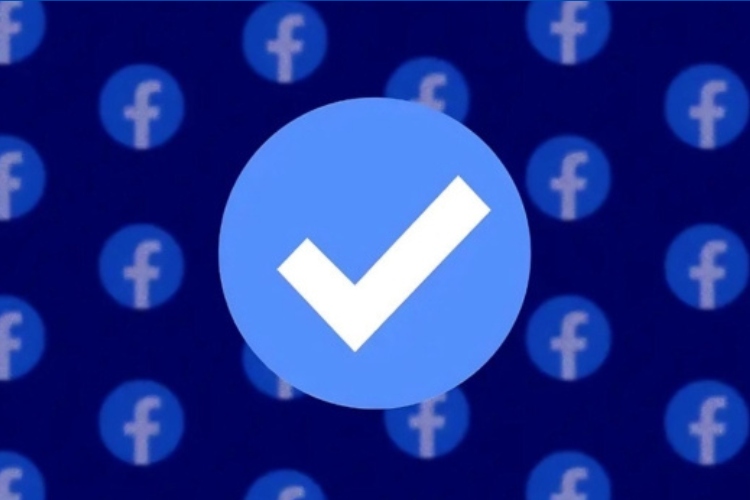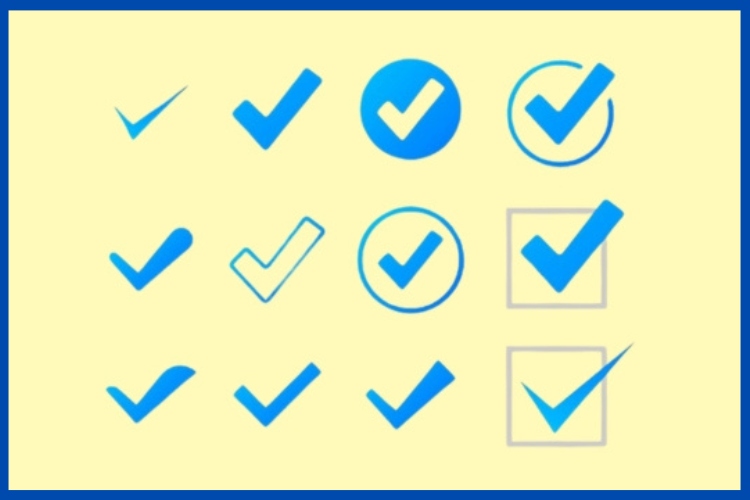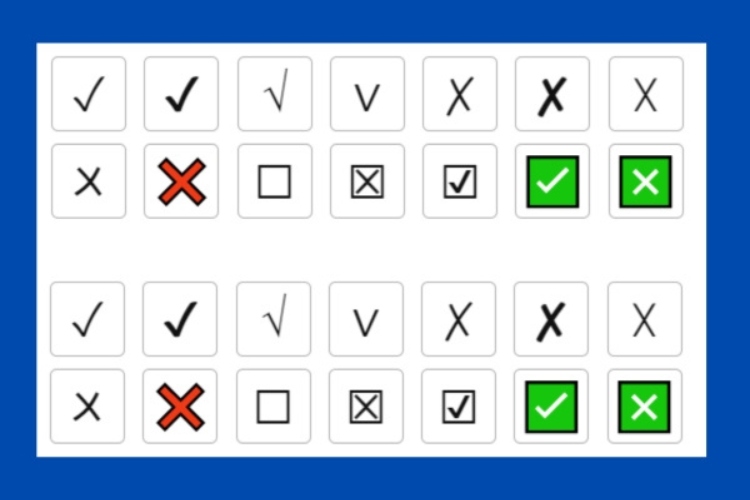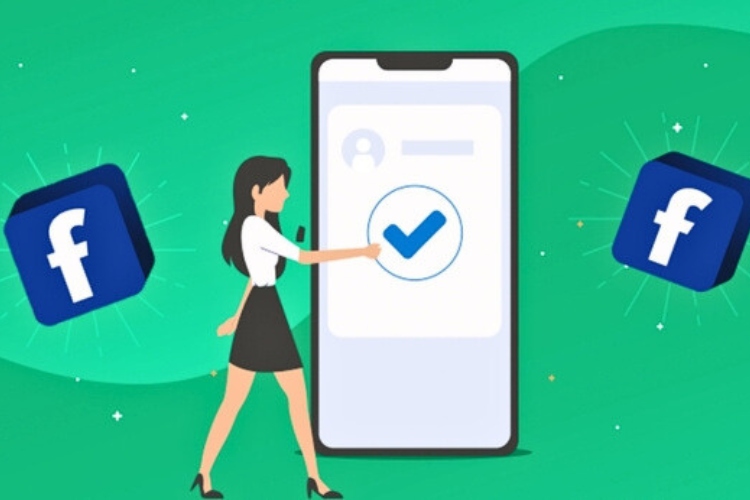
777+ kí tự tích xanh đẹp trên Facebook, TikTok, Telegram không thể bỏ lỡ
Kí tự tích xanh là biểu tượng hình chữ "V" cách điệu hoặc dấu tick, thường được hiển thị dưới dạng: ✅, ✔️, hoặc ✓. Hơn nữa, kí tự tích xanh cũng là biểu tượng thể hiện sự xác minh, uy tín và chuyên nghiệp, thường thấy trên Facebook, TikTok hoặc tên game. Bộ sưu tập 777+ kí tự tích xanh đẹp trên Facebook, TikTok, Telegram dưới đây từ Mobifonts sẽ giúp bạn dễ dàng copy dấu tích xanh và dùng ở bất cứ đâu.
Kí tự tích xanh là biểu tượng hình chữ “V” cách điệu hoặc dấu tick, thường mang ý nghĩa xác minh, đã được công nhận hoặc chứng thực. Các kí tự dấu tích như ✅, ✔️, ✓ giúp thể hiện sự đồng thuận, chính xác và được sử dụng phổ biến trong các nền tảng mạng xã hội như Facebook, TikTok, Telegram hay trong các trò chơi online. Người dùng thường copy dấu tích xanh để tạo sự uy tín cho nickname, tiểu sử, mô tả tài khoản hoặc bio cá nhân.
Dưới đây là bộ icon dấu tích xanh đẹp phù hợp để sử dụng trên Facebook, TikTok, Telegram hoặc các nền tảng mạng xã hội khác. Bạn có thể dễ dàng copy các dấu tích xanh này để sử dụng. Các biểu tượng này tương thích tốt với hầu hết nền tảng như Android, iOS, Windows, Facebook, TikTok hay các tựa game như Free Fire, Liên Quân. Sau đây là danh sách dấu tích xanh đẹp nhất 2025:
Nếu bạn muốn tạo tên hiển thị ấn tượng và cá tính, bộ sưu tập chữ kí tự tích xanh dưới đây sẽ là lựa chọn lý tưởng. Từ dễ thương đến ngầu lạ, mỗi kiểu chữ đều mang phong cách riêng, giúp bạn nổi bật ngay lập tức. Cùng khám phá và chọn mẫu phù hợp nhất.
Trên Facebook, nhiều người thường sử dụng chữ kiểu “dấu tích xanh” để làm nổi bật nội dung bài đăng, tiểu sử, hoặc bình luận. Dưới đây là một số kiểu chữ phổ biến và được ưa chuộng nhất 2025:
Các kiểu ký tự chữ tích xanh hoặc biểu tượng tích xanh đều có thể làm nổi bật tên tài khoản, kênh, hoặc tiểu sử (bio) trên Tiktok. Dưới đây là các kiểu ký tự chữ và biểu tượng "tích xanh" phổ biến nhất:
Trên Telegram, người dùng thường sử dụng các biểu tượng tích xanh hoặc kiểu chữ dấu tích xanh nghệ thuật để tạo điểm nhấn cho tên hiển thị, tiểu sử. Một số kí tự tích xanh dạng chữ được sử dụng nhiều nhất trên Telegram bao gồm:
Nếu bạn còn băn khoăn về cách sử dụng kí tự tích xanh, phần dưới đây sẽ giải đáp những thắc mắc thường gặp và giúp bạn hiểu rõ hơn khi áp dụng vào thực tế.